Font Seri Atlanta
Diterbitkan: 2023-03-30Mengalami kesulitan menemukan font yang sesuai dengan proyek desain grafis Anda berikutnya? Apakah Anda mencari font yang sesuai dengan tagihan dalam segala hal? Serial Atlanta telah melejit selama beberapa tahun terakhir berkat font tertentu yang digunakan pada poster serial tersebut.
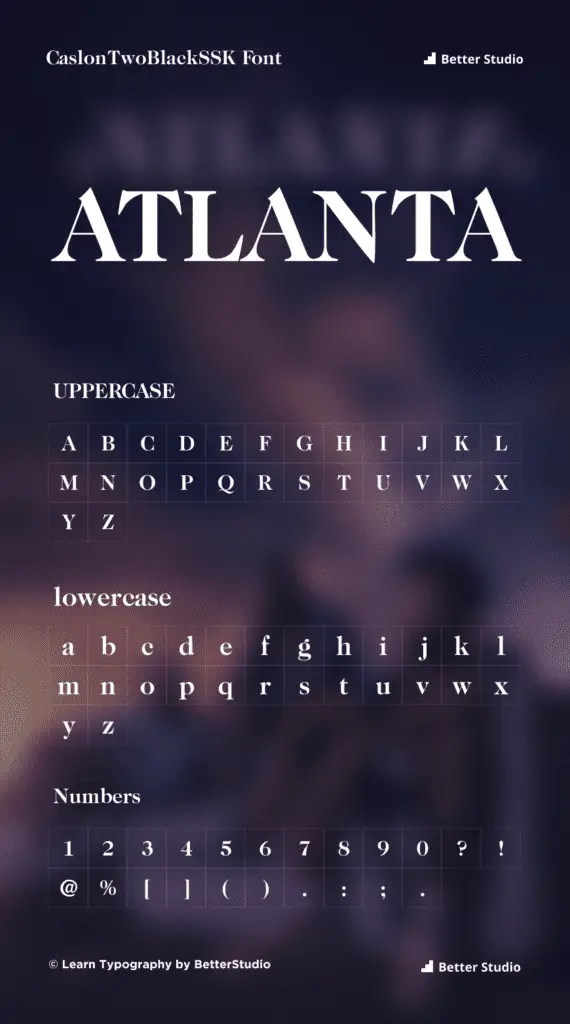
Font Apa yang Digunakan Atlanta?
Ada font bernama " CaslonTwoBlackSSK " di poster Atlanta.
Karena font Atlanta adalah versi salin dan tempel, Anda tidak memerlukan pembuat font untuk mengonfigurasi desain Anda mirip dengan Atlanta. Namun, jika Anda ingin menyesuaikan desain Anda mirip dengan Atlanta, Anda perlu menggunakan pembuat teks Atlanta.
Selain itu, Anda dapat menggunakan semua karakter abjad dan numerik yang diperlukan untuk desain Anda dan tidak akan dibatasi dengan cara apa pun.
Alternatif dan Gaya Font Mirip dengan CaslonTwoBlackSSK
Anda telah datang ke tempat yang tepat jika Anda mencari font alternatif yang memiliki gaya dan desain yang sama dengan CaslonTwoBlackSSK yang dapat Anda gunakan.
Berikut adalah daftar lima:
- font Montserrat
- jenis huruf Helvetica
- font Avenir
- jenis huruf Times New Roman
- Fon Futura
Font Atlanta Didesain oleh Desainer Yang Mana?
Jason Anthony Walcott , salah satu desainer grafis terkemuka yang berspesialisasi dalam mendesain tipografi, menciptakan font Atlanta, menyebutnya sebagai salah satu yang paling terkenal.
Rentang font ikoniknya termasuk Impact, Helvetica, Museo Sans, di antara banyak lainnya, dan dia adalah salah satu desainer terkemuka dunia.
Di tahun 80-an, Walcott mulai mendesain font untuk majalah dan surat kabar sebagai bagian dari karirnya sebagai ilustrator.
Selama karirnya, dia telah merekam puluhan album, termasuk debutnya Impact, yang dianggap sebagai salah satu hit terbesar tahun ini dalam hal penjualan.
Hari ini dia telah tampil di media besar seperti The New York Times, The Wall Street Journal, Wired dan The Guardian.
Walcott dianggap oleh banyak orang sebagai salah satu desainer paling berpengaruh dalam beberapa dekade terakhir dan terus menghasilkan tipografi unik untuk berbagai merek hingga saat ini.
Setelah menjadi terkenal dengan pemandangan seni jalanan Atlanta yang semarak, yang, seperti yang mungkin Anda ketahui, dihiasi dengan CaslonTwoBlackSSK, font resmi kota, banyak dari mural cantik ini menampilkan font ini.
Telah ada penggunaan font serif yang tebal dan geometris seperti ini selama beberapa dekade sekarang untuk memberikan rasa identitas pada kota secara keseluruhan, terutama di daerah perkotaan.